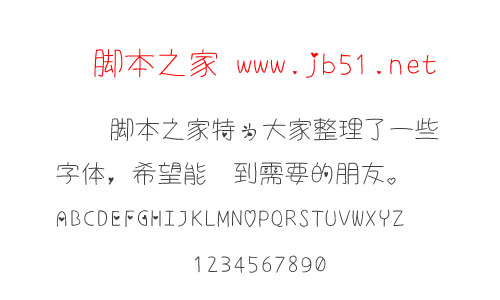
S2G_love字體是一款非??蓯鄣男男沃形淖煮w,并且不管是文字、字母還是符號,只要是帶有點的字符,基本上都會以心形來顯示,非??蓯?,通常用戶喜歡稱之為s2g love字體,該字體非常有愛,帶有心形圖案,并且擁有卡通效果,可用于卡通設計、廣告設計、平面設計、印刷包裝、報紙雜志等行業(yè),使用時請選擇“s2g love”即可,歡迎有喜歡或需要此字體的朋友們前來下載使用。